Tipografía en papel de Jérôme Corgier desde París
Jérôme Corgier juega con el papel para dar forma a unas tipografías tridimensionales, con una realización a medio camino entre las maquetas de arquitectura, la ilustración y el lettering. Fundador del Atelier Pariri, el diseñador gráfico francés se confiesa fascinado por la escultura y la tipografía, y es precisamente la mezcla de ambas la seña de identidad de sus trabajos.
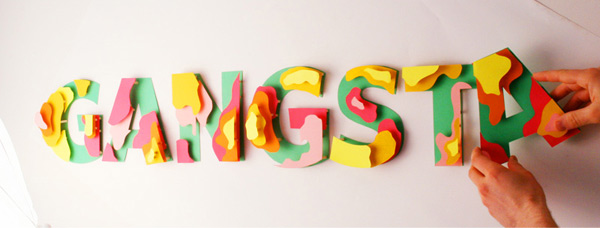
Detalle de la maqueta construida para dar forma a las tipografías.
Para producir estos ‘bodegones de letras’ el diseñador emplea principalmente papel que integra otros materiales como la madera o el metal. El papel ya sea rasgado, doblado o superpuesto se convierte en la materia prima de volúmenes, estratificaciones y efectos visuales que dan vida a formas reconocibles y legibles.
Abecedario Space Typography.
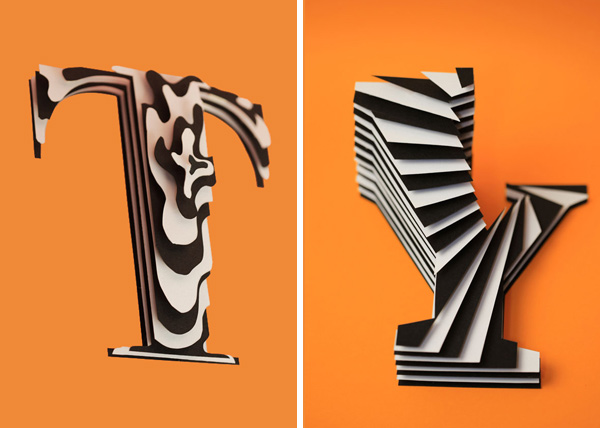
Abecedario Space Typography.
Abecedario Space Typography. El montaje exige que la letra se sitúe tumbada.
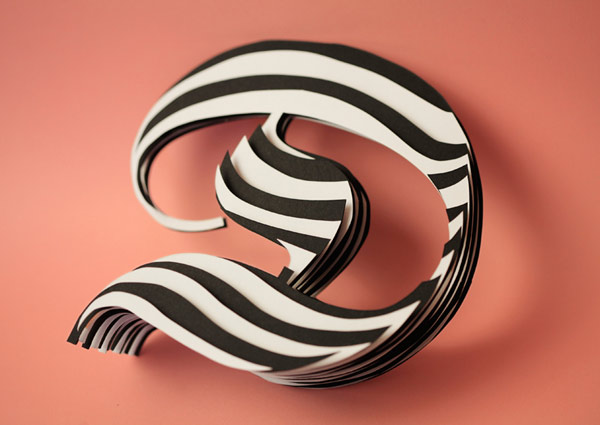
Abecedario Space Typography.
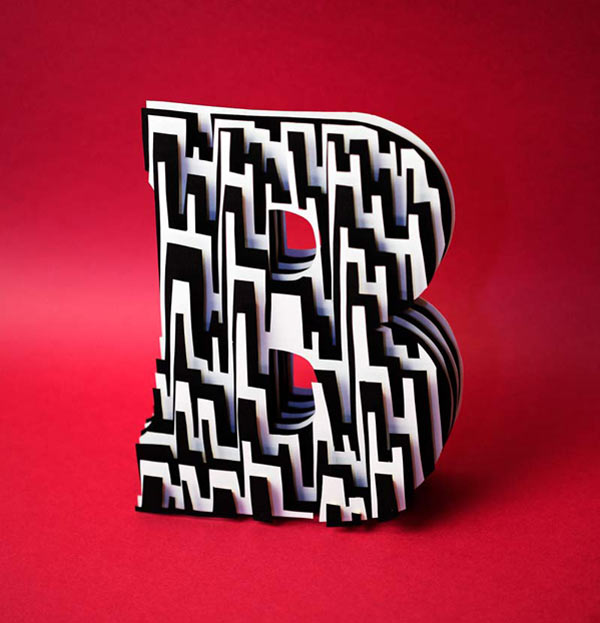
Abecedario Space Typography.
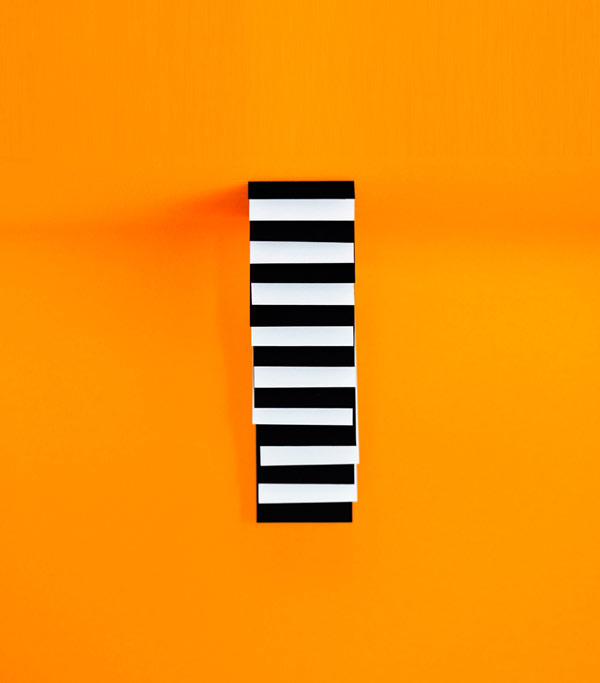
Abecedario Space Typography.
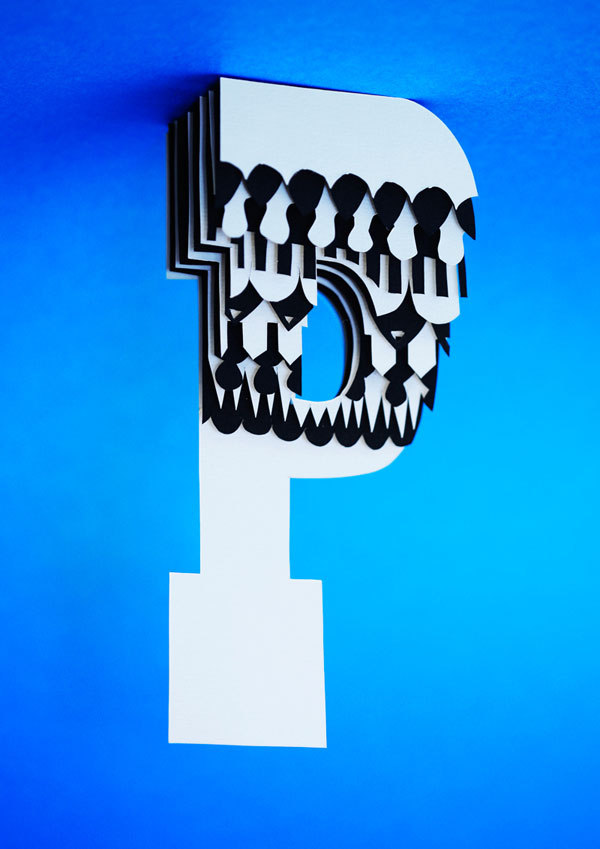
Abecedario Space Typography. La fotografía se toma invertida para visualizar correctamente la letra.
Ilustración Circus.
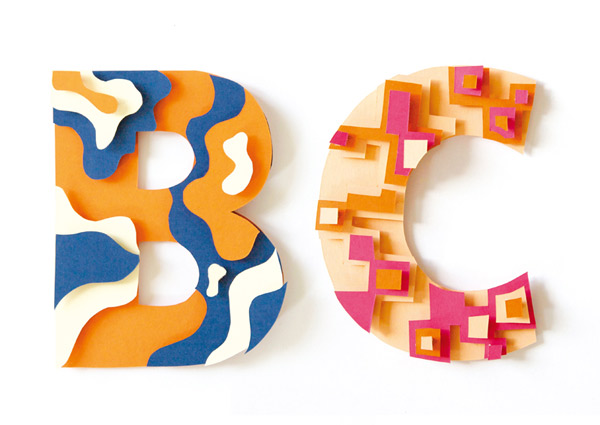
Proyecto personal, letras incluidas en Story, Jérôme Corgier.
La letra nace de un instante fotografiado, Jérôme Corgier.
Space Type.
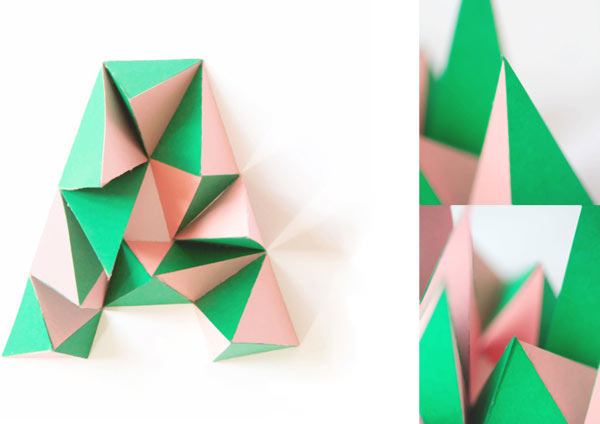
That, proyecto personal, Jérôme Corgier.
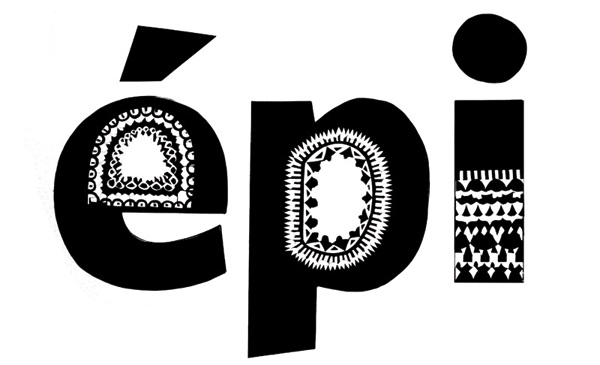
Creaciones tipográficas para la revista gastronómica 'Capharnaüm'. El material y la tipografía escogida representan distintos gustos y palabras relacionadas con la cocina como épicé (especiado).
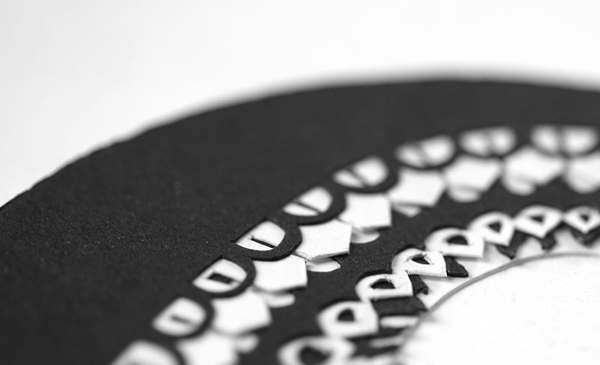
Creaciones tipográficas para la revista gastronómica Capharnaüm.
Eye, proyecto prsonal, Jérôme Corgier.
Flux, proyecto personal, Jérôme Corgier.
Propuesta para Nike, Jérôme Corgier.
Propuesta para Adidas, Jérôme Corgier.
Propuesta de portada de la revista de estilo del New York Times (dcha.) y X, proyecto personal (izq.), Jérôme Corgier.
Dune, proyecto personal, Jérôme Corgier.
Paper Drop Cap, Jérôme Corgier.
Detalle de Paper Drop Cap, Jérôme Corgier.
Paris, proyecto personal, Jérôme Corgier.